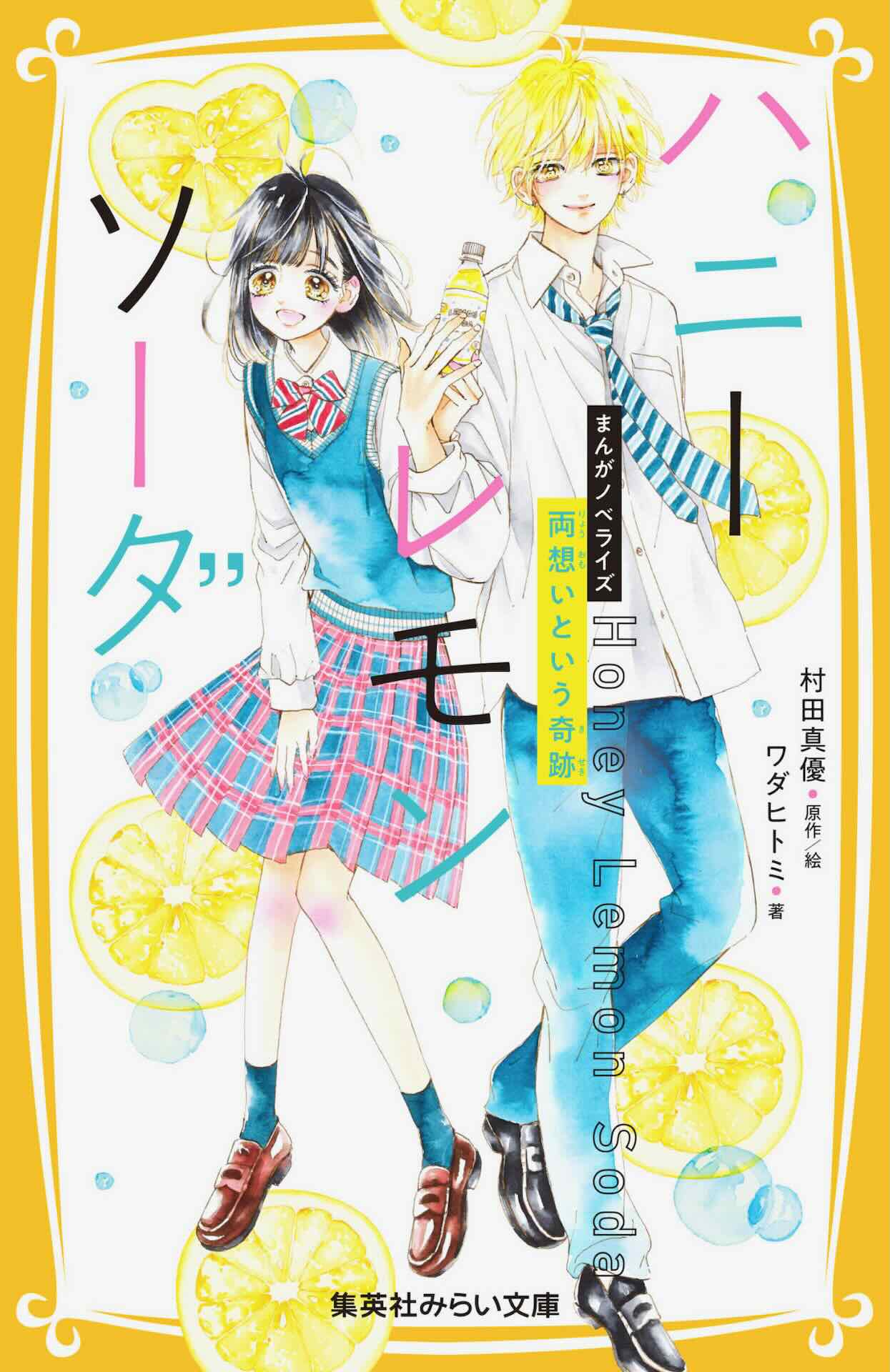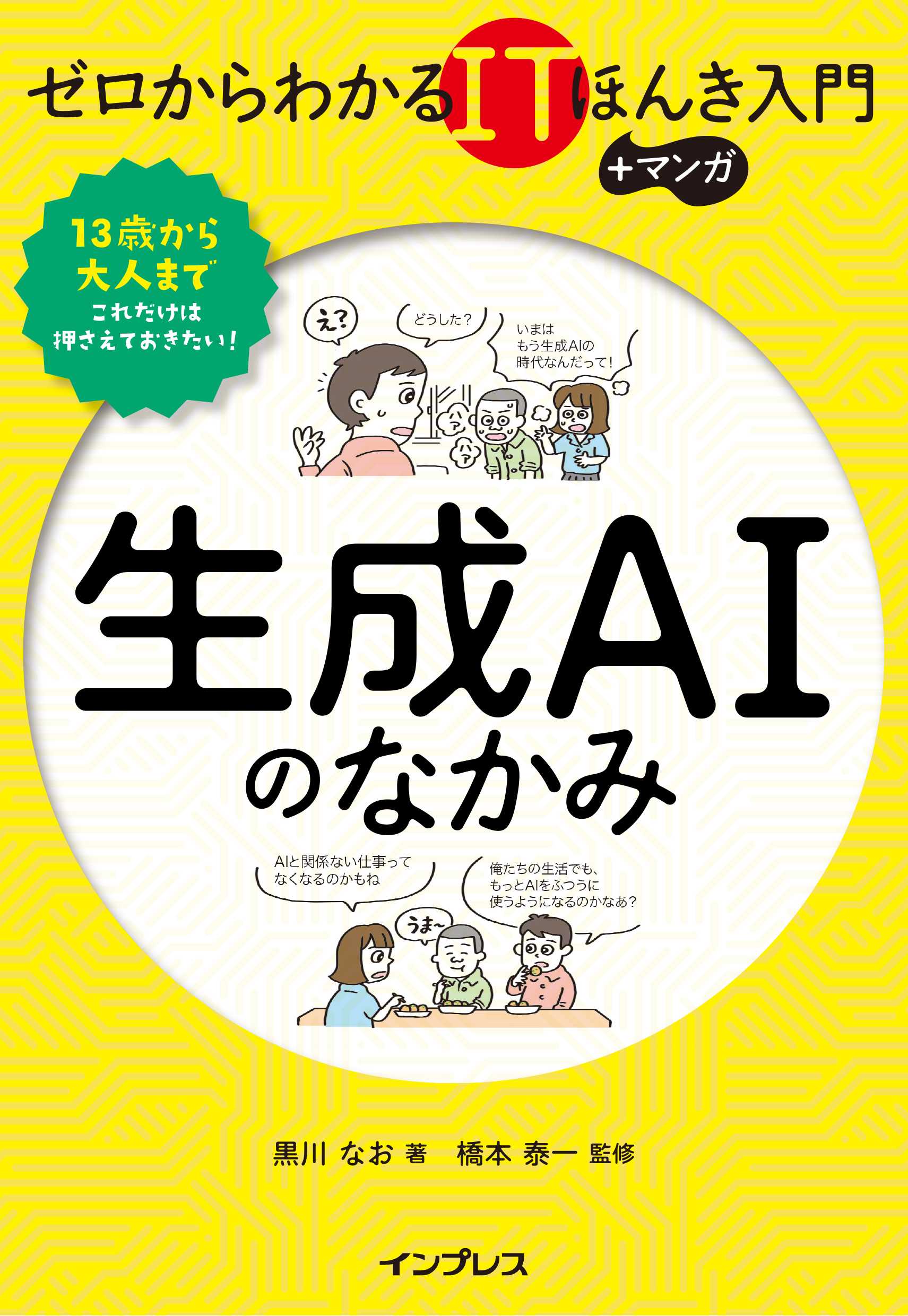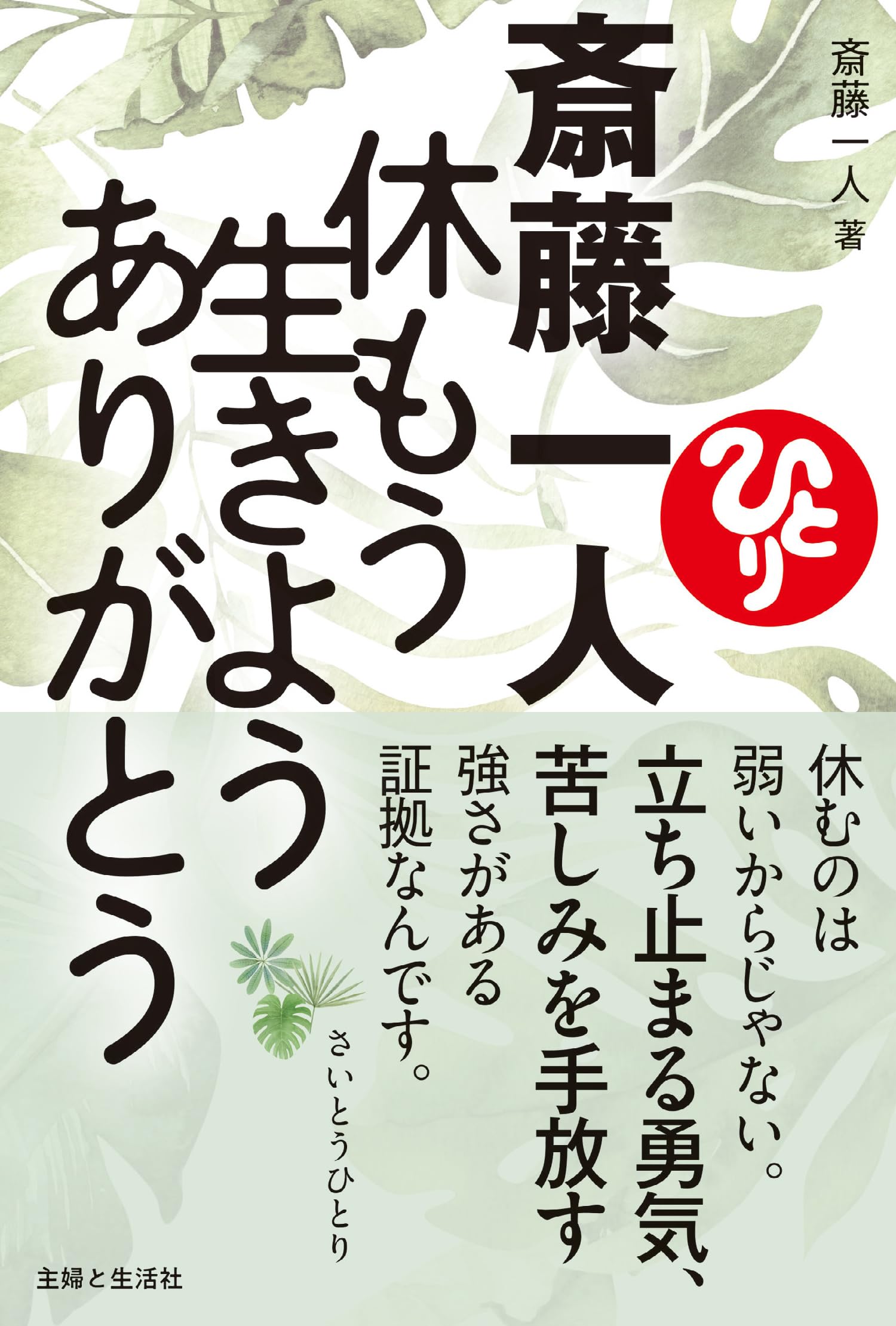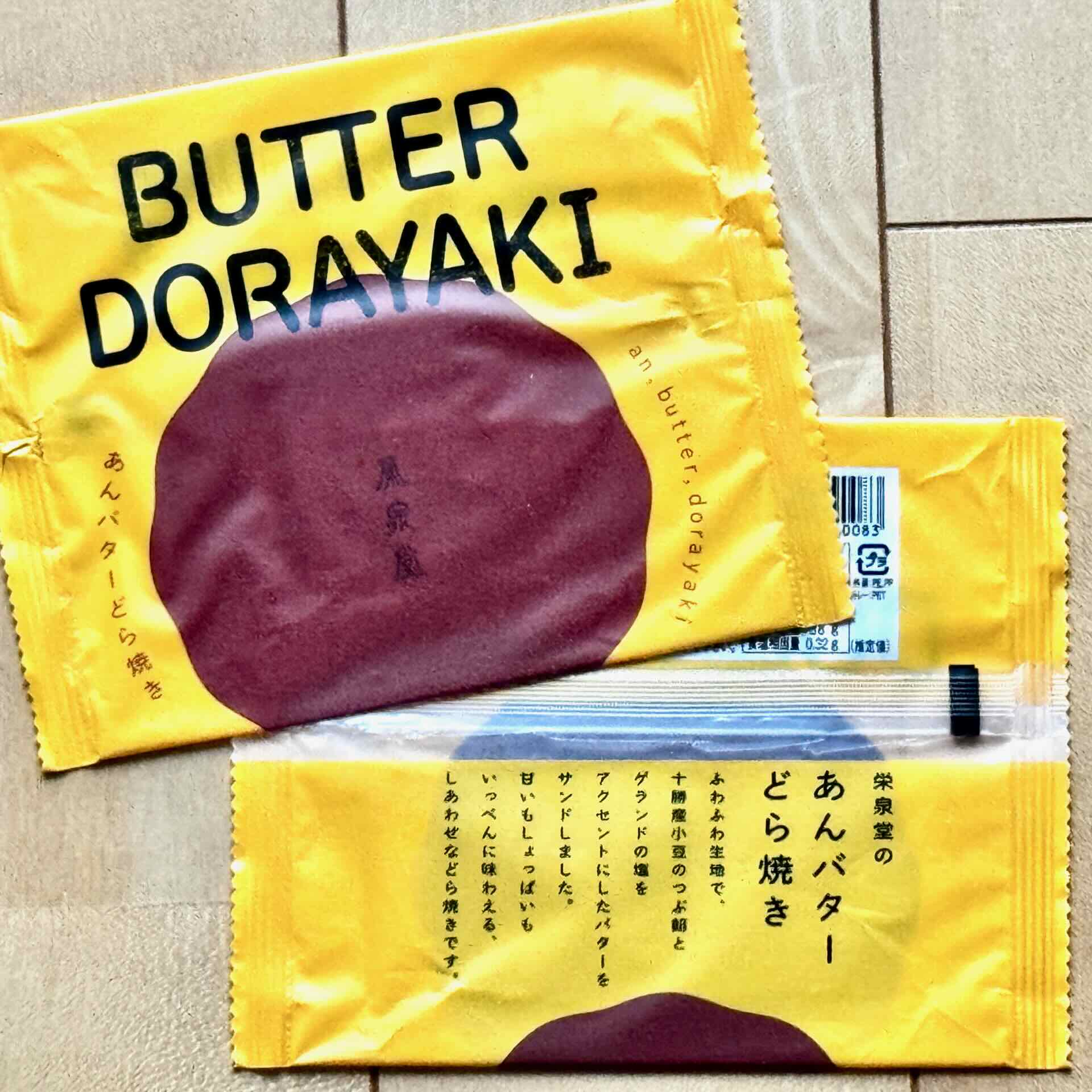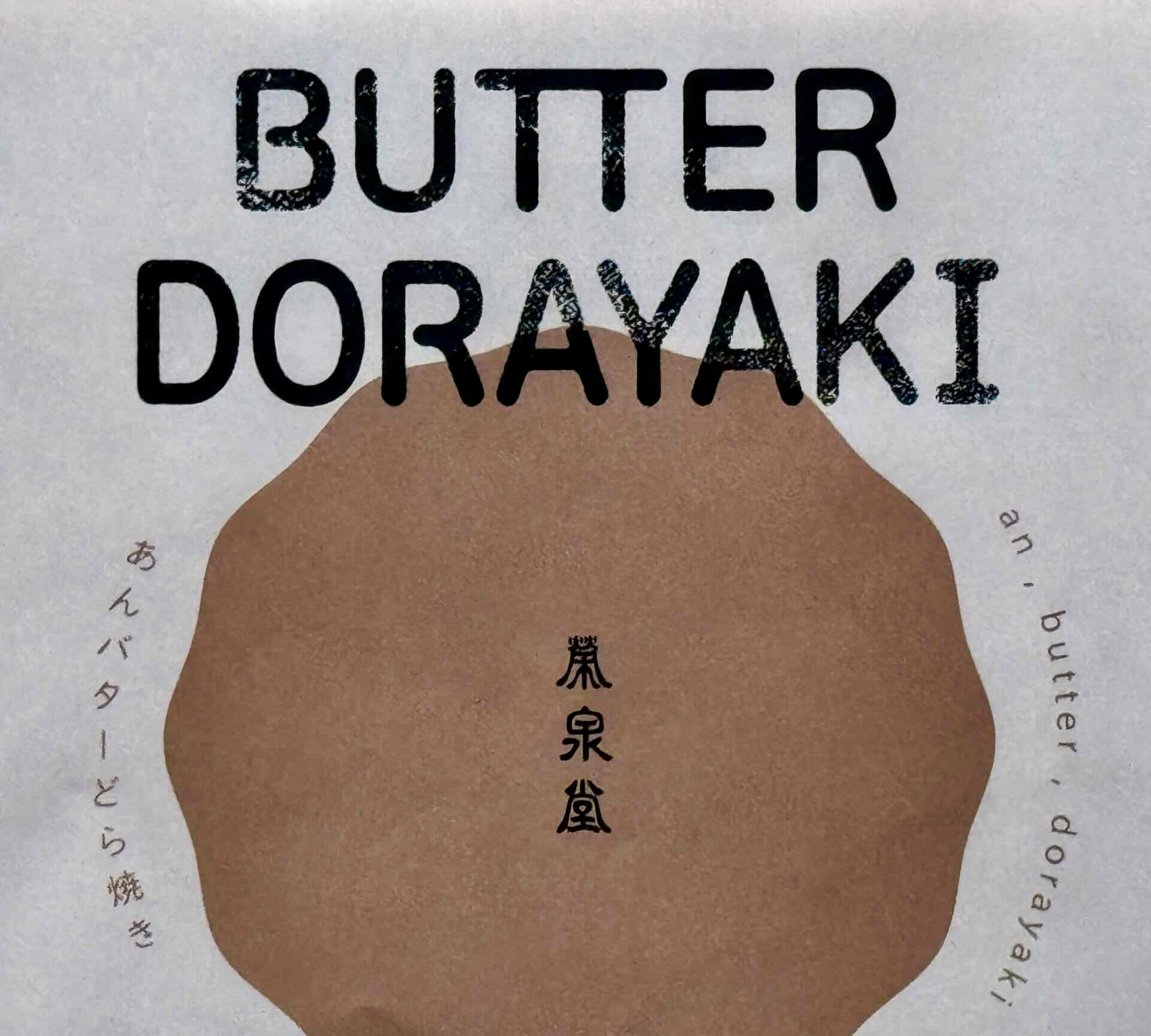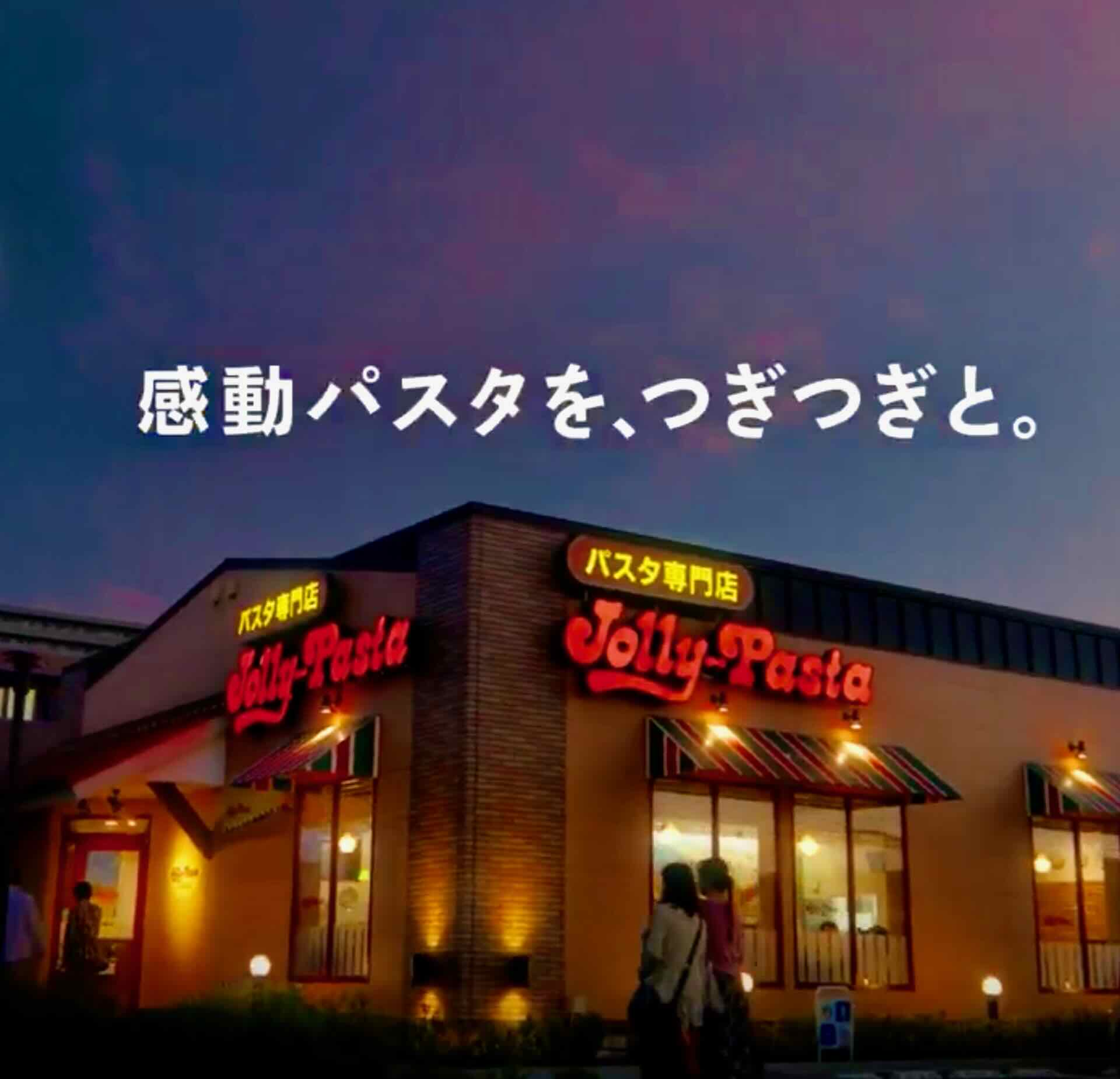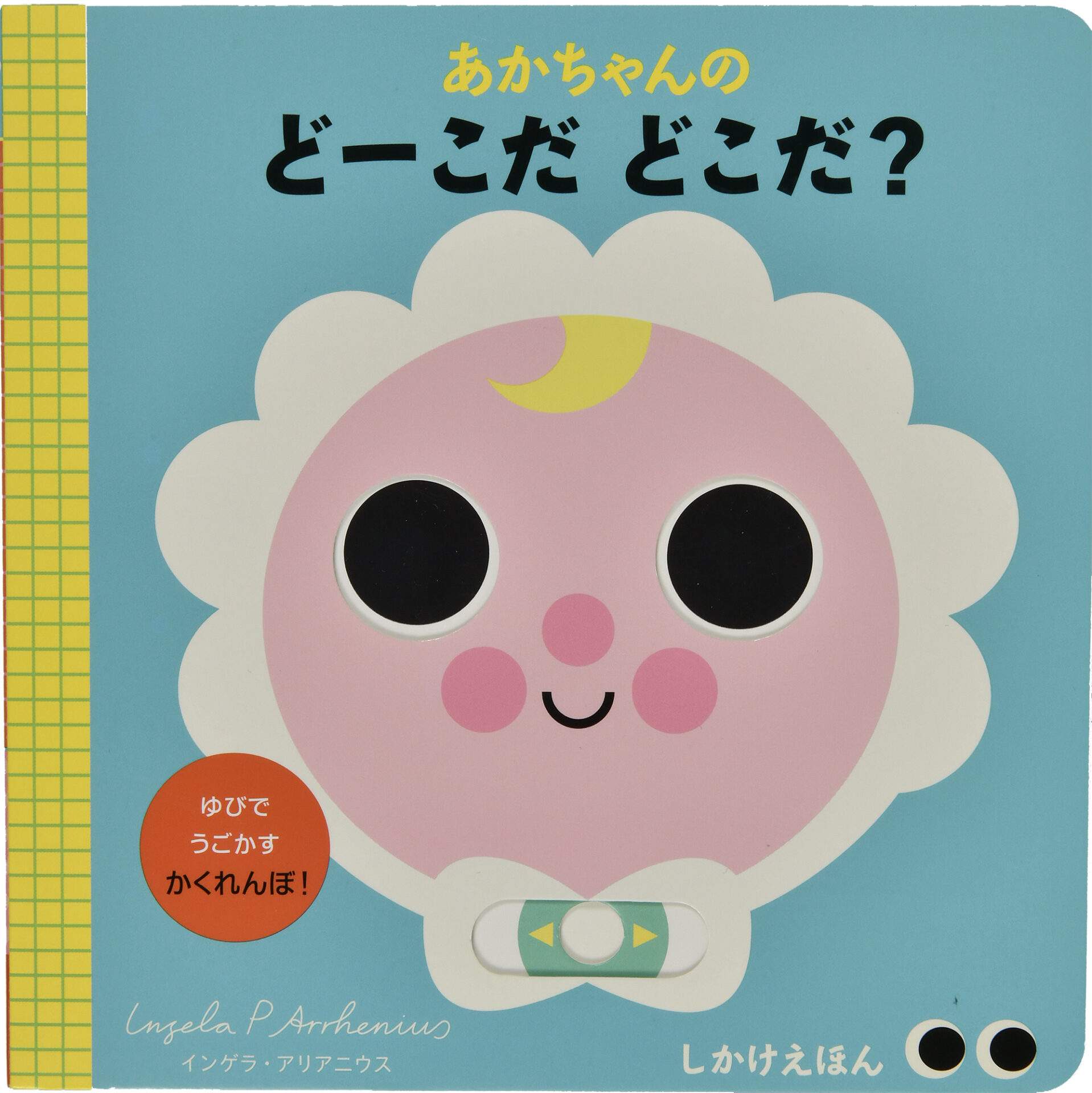
フォントワークスやモリサワから販売され親しまれている、かな書体「墨東」
本家本元タイプラボの、総合書体「墨東ルイカ」「墨東レラ」もヨロシク!
本の表紙 さとうゆたか
書名:せんんそうを はしりぬけた『かば』でんしゃ
著者:間瀬なおかた(作・絵)
発行:ひさかたチャイルド
さとうゆたか
これも。
本の表紙 さとうゆたか
書名:にぎっちゃだめ!
著者:チョー ヒカル
発行:白泉社
「だ」の文字が少しイジられてる…のが、フォント作者からすれば残念。
さとうゆたか
本文ページ。
サムネ?画像 さとうゆたか
JTBの「にっぽんの祭り・花火特集」
墨東レラ-6かな?
テレビCM さとうゆたか
ジョリーパスタの冷製パスタフェア第2弾。
CMの最後にこの文字が現れる…。
あ さとうゆたか
ちょっと大きくした。
みぞれ墨東 さとうゆたか
仙台栄泉堂の「あんバターどら焼き」。
BUTTER DORAYAKIの文字に、みぞれ墨東の英字フォントが使われている。
すこし加工されているが、自分が作ったフォントは、すぐに分かるんだな…。
あ さとうゆたか
英字部分だけ。
10個入りの箱に付いていた、のし紙。
あ さとうゆたか
個別袋の裏の説明文は、しっかりと「みぞれ墨東」。
本の表紙 さとうゆたか
みぞれ墨東の使用例。
書名:休もう生きようありがとう
著者:斎藤一人
発行:主婦と生活社
あ さとうゆたか
こちらは、新聞広告。
テレビCM さとうゆたか
墨東ルイカです。
クリアアサヒ「あなたの一杯はクリアですか?」篇 15秒 北村匠海
これも。
本の表紙 さとうゆたか
みぞれ墨東の使用例。
書名:生成AIのなかみ
著者:黒川 なお、橋本 泰一(監修)
発行:インプレス
さとうゆたか
同じシリーズ。
書名:Web3のなかみ
著者:黒川 なお、橋本 泰一(監修)
発行:インプレス
さとうゆたか
もうひとつ…。
さとうゆたか